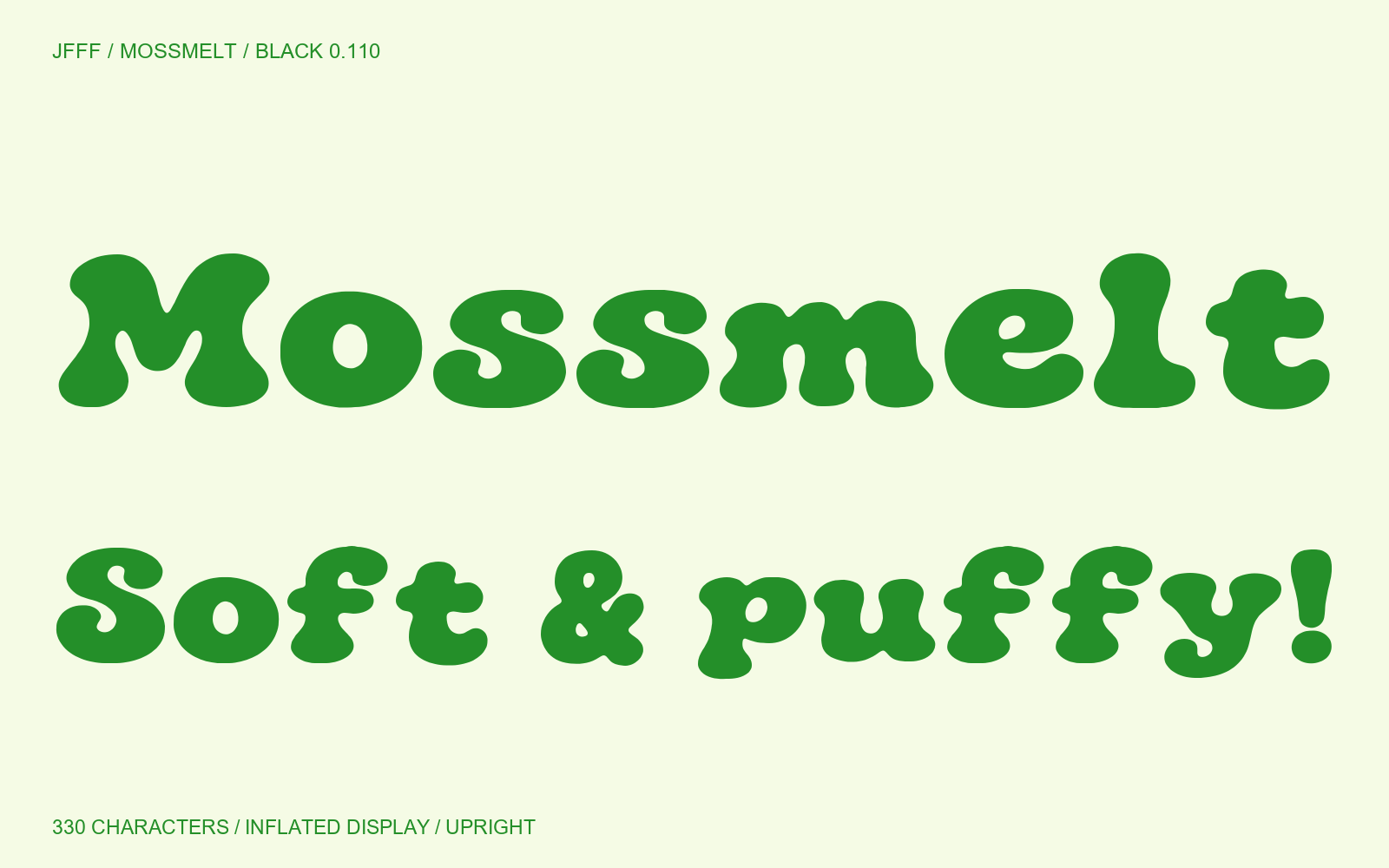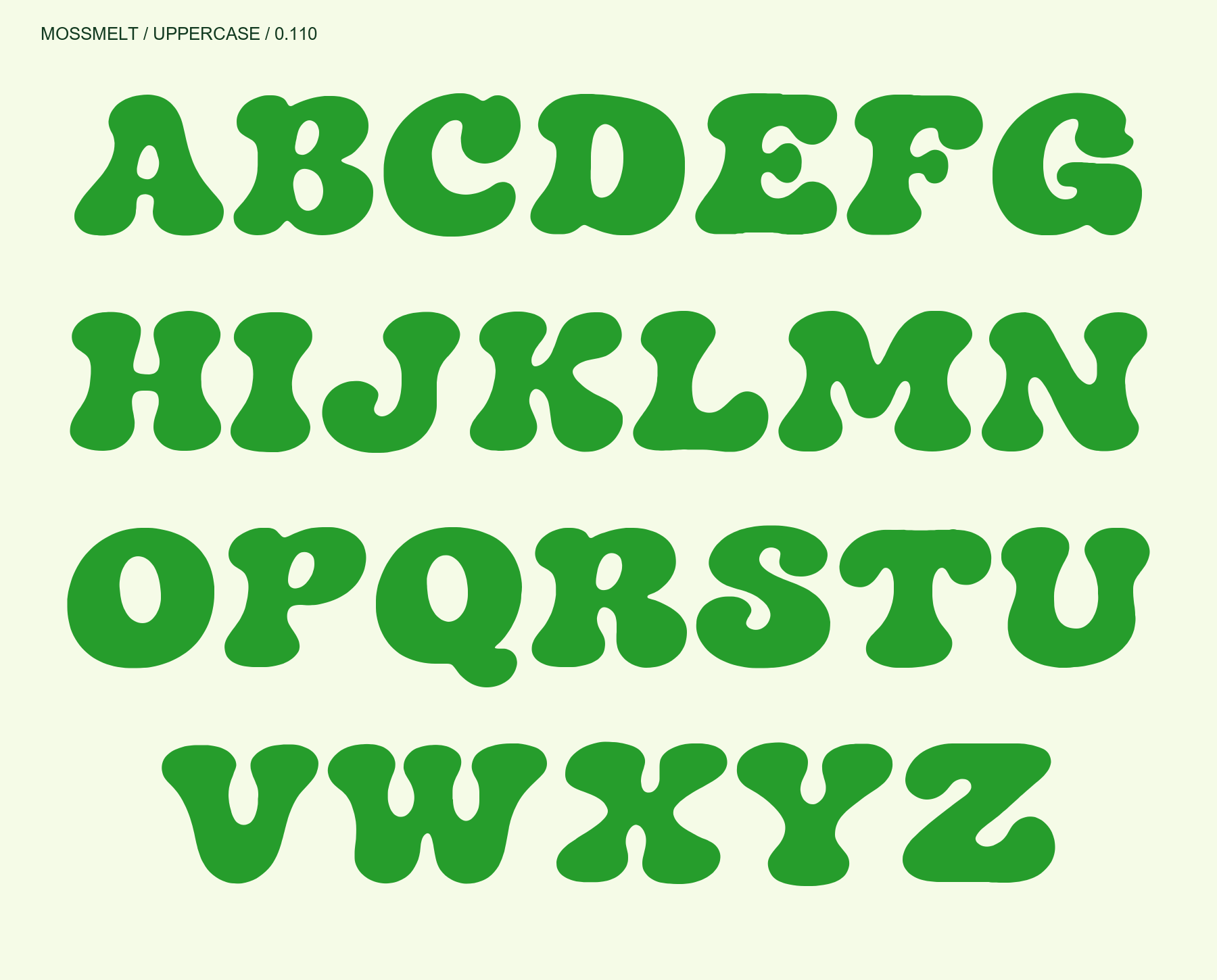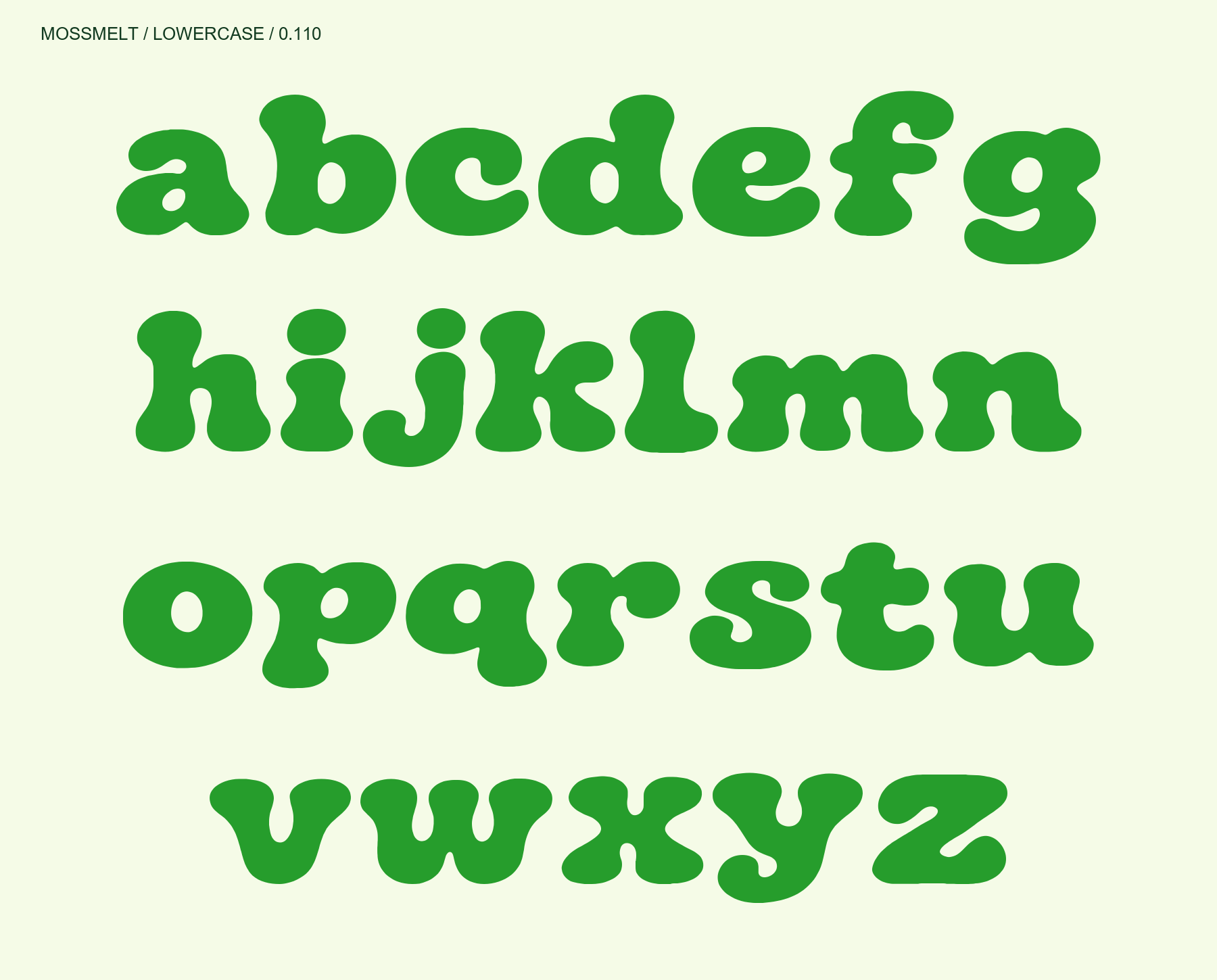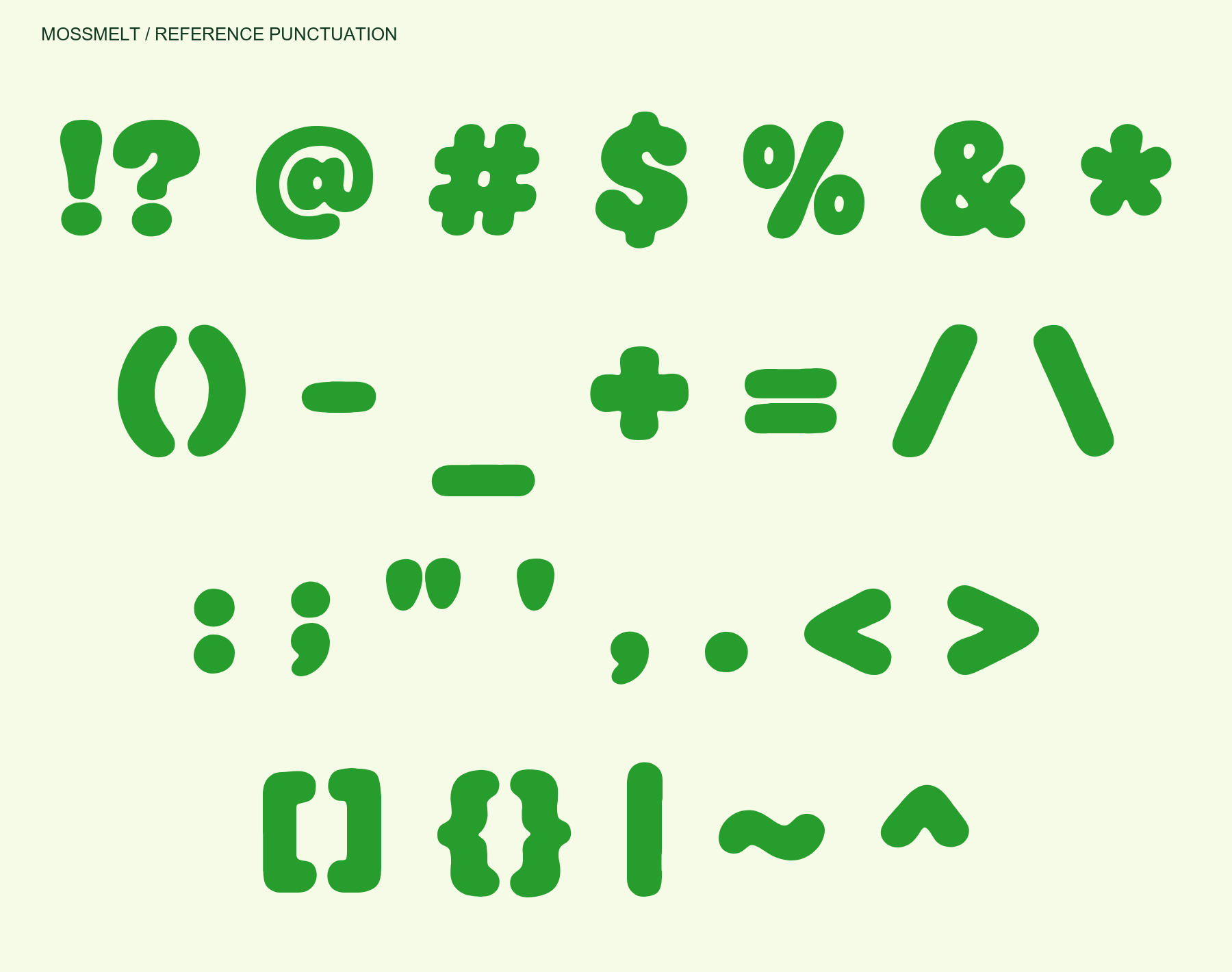
Mossmelt는 넓고 부푼 몸통, 잘록한 줄기, 둥글게 말린 끝과 타원형 속공간이 특징인 초굵은 직립 디스플레이 서체입니다. 영문 대소문자와 기호에 유기적인 곡선을 적용했습니다. Black 0.110 · 라틴 330자(공백 2개 포함). 영문, 숫자, 라틴 확장 문자와 문장부호·통화·연산 기호를 지원합니다. 한글과 독립 결합 악센트는 포함하지 않습니다. 330자 확대 시트 검수 후 숫자 1, 확장 문자와 악센트 등 35자를 조정했습니다. 64px 이상 큰 제목과 패키지에 권장합니다. 0.x 초기 버전이며 운영체제별 설치, 인쇄 및 전체 문자쌍 커닝 검증은 완료하지 않았습니다.